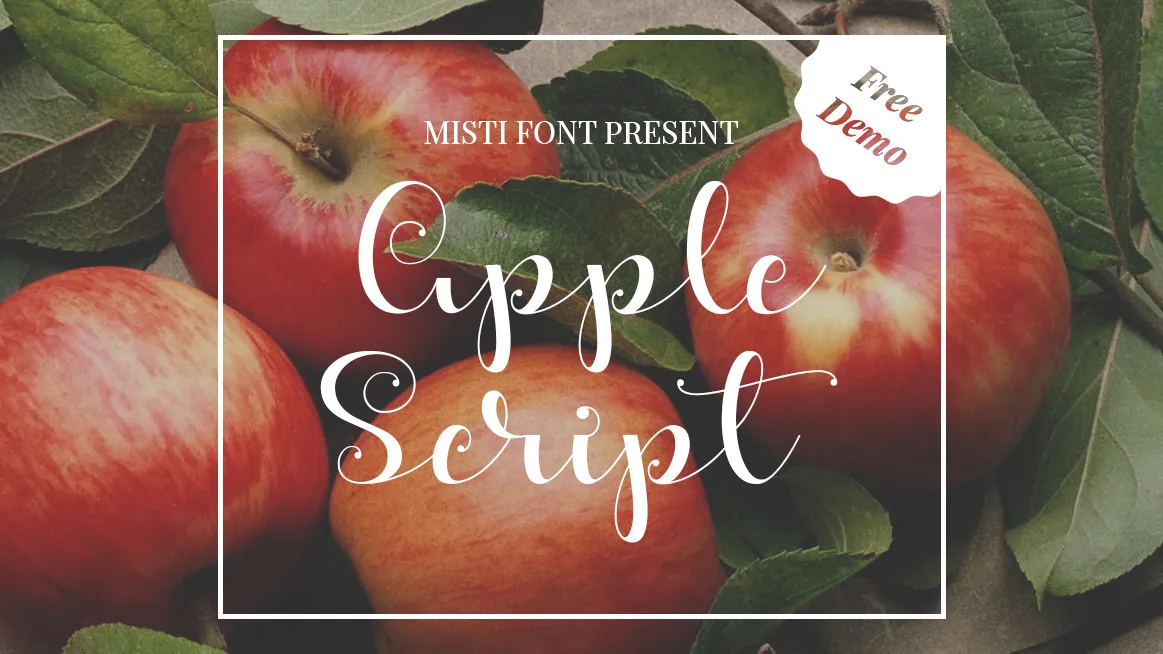
Apples Script Font – Download Grátis
A Misti’s Fonts apresenta “Apples Script Font”, uma fonte criada especialmente para os amantes do design. Este script é perfeito para designers que procuram um tom elegante e sofisticado para seus projetos digitais. Com linhas leves e proporções bem balanceadas, a “Apples Script Font” não apenas oferece aparência minimalista e moderna, mas também uma versatilidade incrível para diversas aplicações de design. Ideal tanto para textos profissionais quanto para designs gráficos digitais, esta fonte é certamente um investimento valioso para qualquer designer que busque qualidade e elegância em suas criações. Se você busca uma opção confiável para seu trabalho no mundo digital, “Apples Script Font” é uma ótima escolha.
Designer: Misti’s Fonts